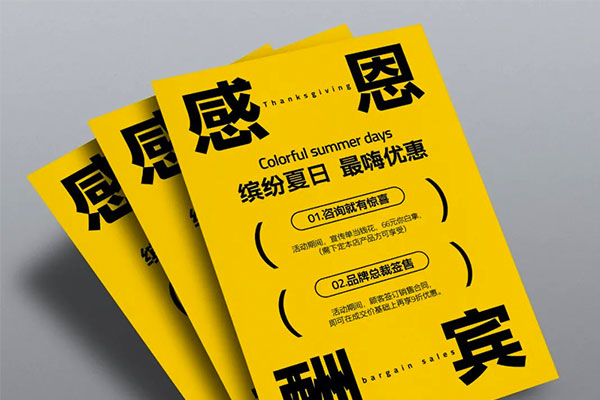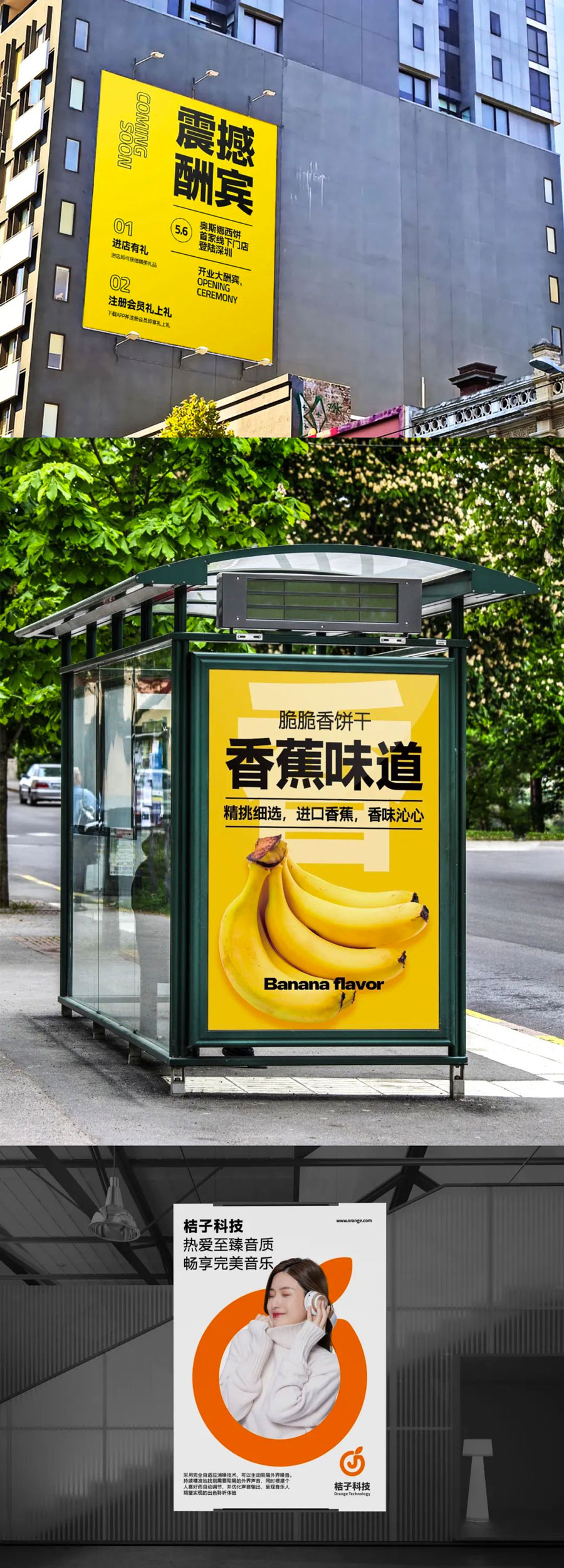
字体圈伟君黑
字体圈伟君黑是字体圈推出的第四款免费商用字体,前面发布的有 字体圈欣意吉祥宋 字体圈欣意LOGO体 字体圈欣意冠黑体
其中不得不说就是 字体圈欣意冠黑体 ,这款字体的流传度很高,自由君就发现经常会在自媒体、短视频、广告中看到。
字体圈伟君黑拥有3字重,基本足够日常使用了。
那么接下来看看我们的新字体,应作者请求,字体名希望加上作者姓氏或名字,作者本意希望起名《字体圈蔡伟君锦黑体》或《字体圈蔡黑体》,但我觉得要么太长,要么不够顺口,最后共同确认下,《字体圈伟君黑》诞生了。
字体作者 :蔡伟君 伟君黑设计师
蔡伟君,从事设计行业十余年,目前就职于深圳一家IT公司设计总监,有丰富的设计实践经验,曾服务过一些大型企业业务,诸如腾讯、OPPO、北汽、新疆农信等设计项目。
我的话:蔡老师的想法其实跟我或者跟很多字体设计师是同样的想法,希望留下点东西在这个世界上,其他设计作品随着时间也许有一天终将会消失,但是字体是可以延续的。《字体圈伟君黑》可以说是我一点点看着做完的,我本身对正文黑体的研究不是很深,也不敢轻易去做,所以这个字体我基本没有给蔡老师很多的修改意见。
其实最开始的时候,蔡老师说很喜欢森泽黑体,想要参照森泽黑体做一款黑体字,我表示市面上的免费商用的黑体字已经很多了,可能做出来了使用者不多,没什么市场,但是蔡老师表示很喜欢森泽的笔形,对黑体字研究颇深,坚持想要做一款黑体字,最后我还是答应了,前前后后花了将近两年时间。花两年时间做一款意料不到将来的免费字体,不得不说蔡老师真的很喜欢字体,也真的很伟大。
字体圈伟君黑